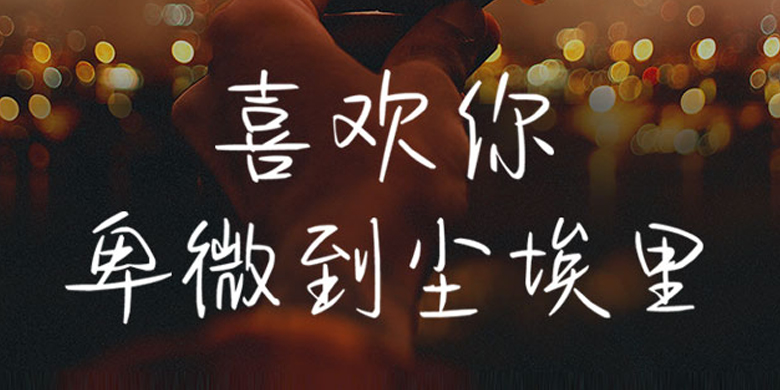
方正手迹-喜欢你卑微到尘埃里
字体品牌: 方正手迹 设计师:俞亦婷 字体分类:创意书写 字体属性:精品字 字符集:简繁扩展(GBK) 发布时间: 2020
喜欢你卑微到尘埃里是一款行书体。该字体结构平稳中正,笔画分布均匀,错落有致。适用于文艺类的书刊、品牌广告和产品包装设计,以及社交网络的个性化用字。